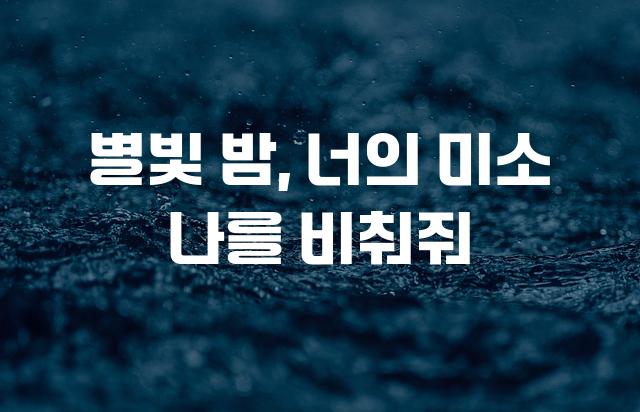
롯데리아 촵땡겨체는 장난스럽고 독특한 특징을 가진 두꺼운 폰트로, 동글동글한 귀여움이 묻어나는 디자인입니다. 이 폰트는 일상에 재미와 행복을 더하는 데 적합합니다.
롯데리아 촵땡겨체은(는)
별모양/패턴, 둥근 스타일, 복실복실, 부드러움, 단단함, 자연감성, 감성적인, 장식 스타일, 굵은 고딕, 두꺼운 스타일, 귀여운 스타일 계열의 생김새를 가지고 있으며
소셜 미디어, 카페 메뉴, 디지털 광고 등에서 자주 활용되며, 효과적인 메시지 전달에 적합합니다.
이 폰트는 소매/유통, 라이프스타일, 음식/식음료 분야에 잘 어울리며,
재미있는, 귀여운, 친근한 느낌을 담고 있는 것이 특징입니다.